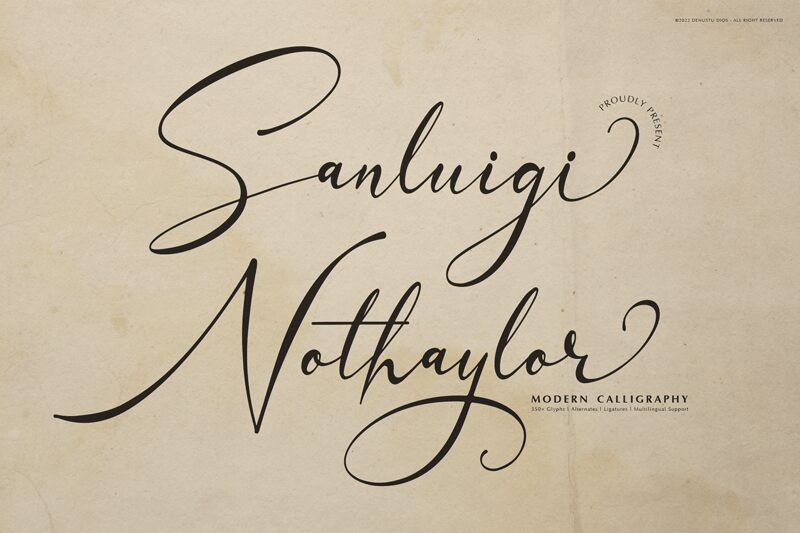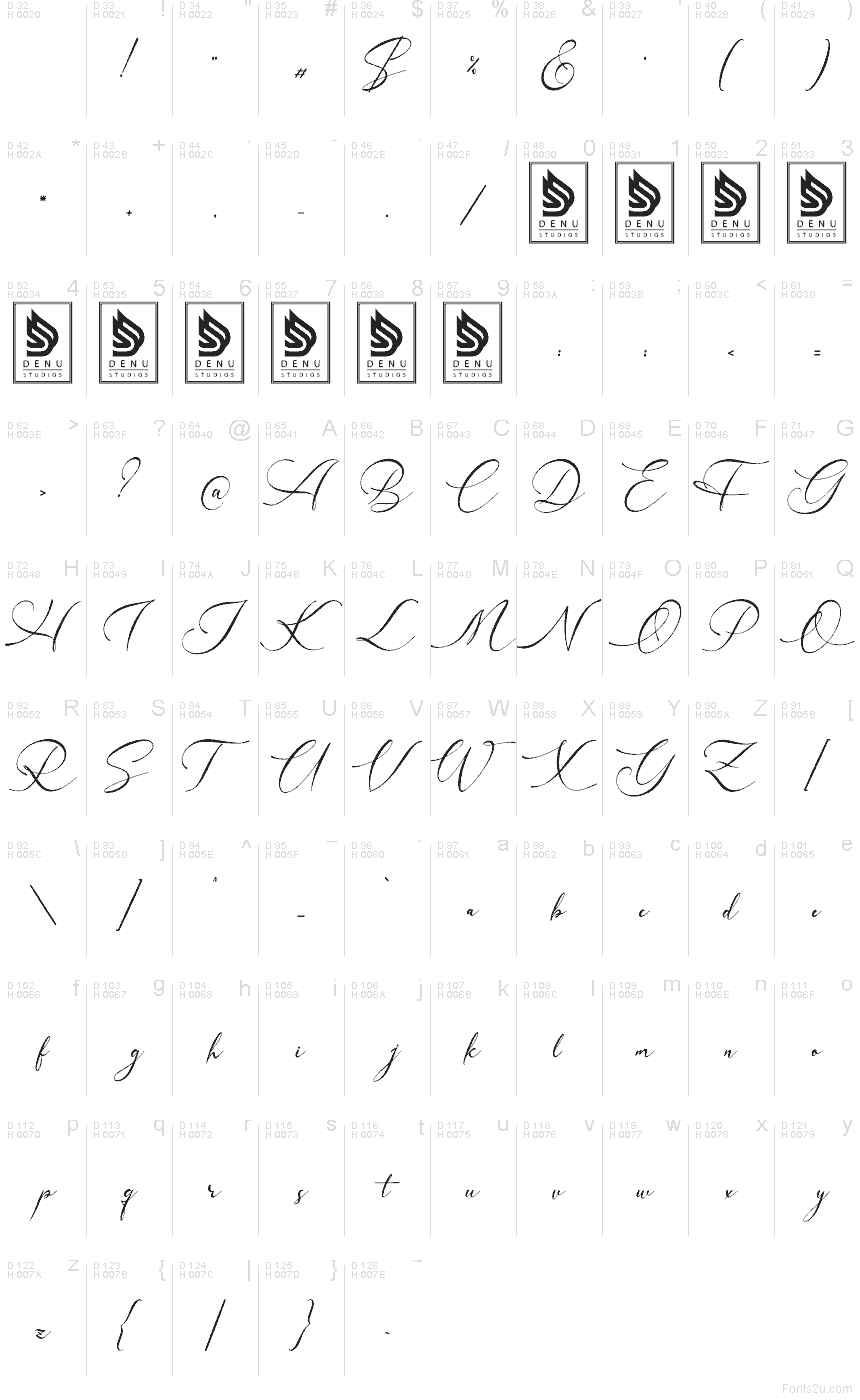
Sanluigi Nothaylor de Denustudios es una tipografía caligráfica gratuita con un aire romántico que recuerda a los bocetos de moda. Las letras nacen de un trazo amplio y expansivo que desemboca en líneas finas y formas entrelazadas, otorgando a la tipografía un ritmo fluido y personal, alejándose de la rigidez de la caligrafía formal.
Es ideal para el branding de boutiques, invitaciones de boda, envoltorios de perfumes, encabezados de redes sociales y titulares de revistas donde el nombre o una frase corta necesiten destacar con elegancia. Al ser una fuente gratuita, también resulta perfecta para bocetos de logotipos, tarjetas de presentación y monogramas, ya que sus trazos de entrada y salida añaden una presencia artesanal incluso a las palabras más breves.